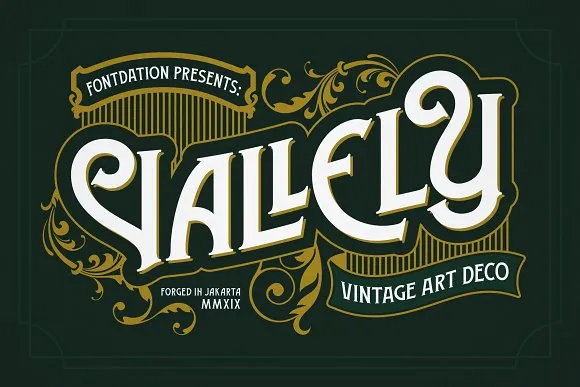
Vallely Vintage Font – Download Grátis
A fonte Vallely Vintage é perfeitamente indicada para quem busca dar um toque nostálgico às suas criações digitais. Esta font é original e foi criada por Twicolabs Fontdation, com uma design inspirado nos enfeites typográficos dos anos 20 que aparecem em embalagens e anúncios antigos. Vallely Vintage se assemelha a um serif art-deco clássico, oferecendo uma variedade de alternativas e combinações de letras para aqueles que valorizam o estilo vintage e art déco. Com 300+ caracteres disponíveis no pacote, esta font é uma excelente adição à sua ferramenta de design digital se você está procurando por um toque de sofisticação clássica. Adicionar a Vallely Vintage à sua coleção irá certamente dar uma nova dimensão e elegância ao seu trabalho.